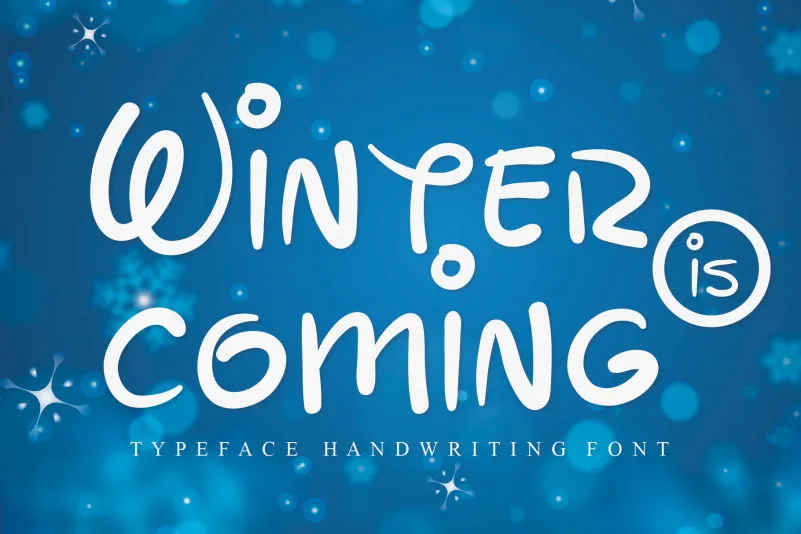
Winter is coming Script Font – Download Grátis
Winter is Coming Script Font é uma fonte escrita a mão que traz um estilo único e divertido para seus projetos criativos. Ela foi feita especialmente para aqueles que buscam algo que seja verdadeiramente autêntico e original no meio de tantas opções digitais disponíveis. Sua elegância cuidadosamente construída oferece uma sensação de conforto e serenidade, perfeita para estilos que valorizam a simplicidade e o equilíbrio. Para designers, criadores de conteúdo e até mesmo amantes da natureza, Winter is Coming Script Font é um trunfo para aqueles querendo dar uma nova cara às suas ideias mais audaciosas. Designado pelo designer andikastudio, esta fonte de escrita a mão oferece tanto os detalhes quanto o encanto que você busca em qualquer projeto visual. Suas linhas fluidas e texturas naturais tornam cada letra única, criando um ar de autenticidade inigualável para seus trabalhos. Seja no design gráfico, na criação de conteúdo digital ou até mesmo na arte ao ar livre, Winter is Coming Script Font se apresenta como uma excelente opção quando você quer que os detalhes falem por si mesmos. Não apenas é uma fonte para fazer um projeto parecer ainda melhor, mas também transmite um toque de natureza e tranquilidade em qualquer layout.